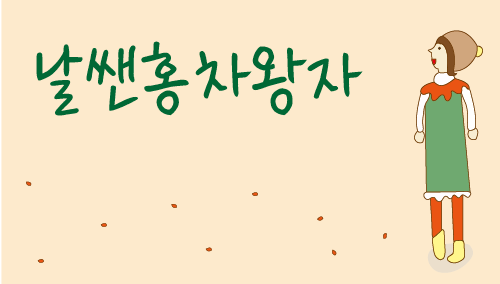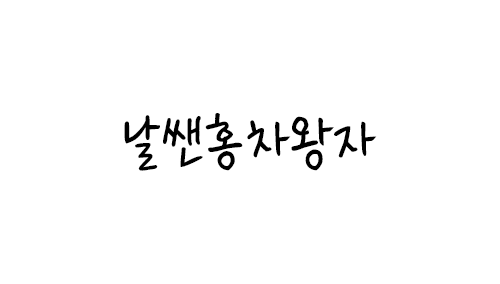
폰트 HU날쌘홍차왕자
굵기 3종
기간 2010
펜으로 썼을때의 느낌을 살린 세로획과 가로획의 두께차가 독특한 서체입니다.
폰트 HU날쌘홍차왕자
굵기 3종
기간 2010
펜으로 썼을때의 느낌을 살린 세로획과 가로획의 두께차가 독특한 서체입니다.
HU날쌘홍차왕자120
HU날쌘홍차왕자130
HU날쌘홍차왕자140